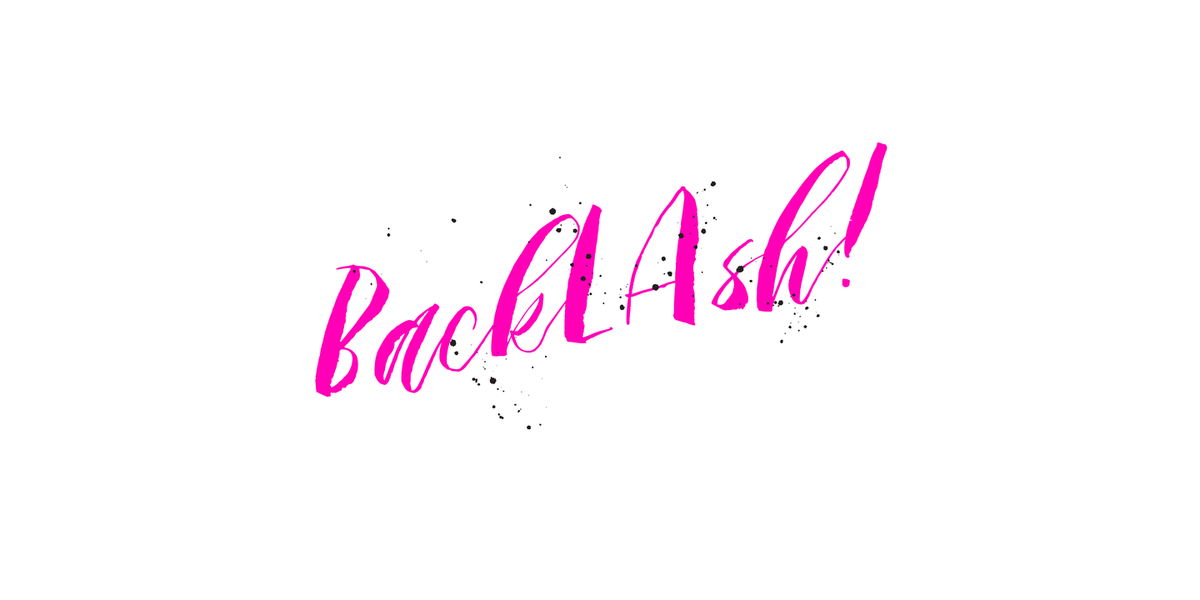
20 fuentes geniales escritas a mano para tus diseños
Cada sitio web tiene un objetivo final: hacer que las audiencias se relacionen con él para que cualquier llamado a la acción que tenga, lo seguirán con entusiasmo. Esto es lo que distingue a muchos sitios web.
Mientras que algunos optan por tomar la ruta más formal para enfatizar su enorme contribución a la industria a la que pertenecen, otros adoptan un enfoque más personal y optan por estar a la altura de las audiencias. Este último es donde las fuentes escritas a mano pueden ayudar mucho.
Las fuentes escritas a mano, desde el propio nombre, se basan en la escritura a mano real de personas. Esto significa que el equilibrio y la simetría pueden no tener nada que ver con su efecto general. Siempre que parezca que alguien lo escribió en un papel con un lápiz en lugar de escribirlo en el teclado de una computadora, se incluye inmediatamente en la categoría de fuentes escritas a mano.
¿Qué hace que las fuentes escritas a mano sean tan atractivas?
En un mundo donde casi todo se ha vuelto digital, a menudo es refrescante ver algo que se creó personalmente. Esta es una de las razones por las que las artes y la artesanía parecen estar ganando un gran número de seguidores en los últimos años. Es algo natural a lo que la gente puede aferrarse en medio de los productos comercializados.
Esto es exactamente lo que ofrecen las fuentes escritas a mano. Da la impresión de haber sido escrito personalmente, lo que hace que todo lo escrito con la fuente parezca más personal, más identificable, más efectivo.
¿Dónde se pueden utilizar estas fuentes escritas a mano? Casi todo, cuando lo piensas.
Los diseñadores que trabajan en blogs y páginas web personales pueden encontrar un gran uso para esto, porque representa mejor a las personas.
Sin embargo, si tiene mucho talento, puede usar cualquiera de estas fuentes escritas a mano incluso si está trabajando en un conjunto de páginas comerciales, especialmente si el propietario del sitio web desea crear una imagen más personal de su marca.
A continuación se muestran 20 fuentes geniales escritas a mano que puede usar para sus diseños. Son ideales para cualquier proyecto de diseño, sin importar el tema o estilo que requiera.
Podrían funcionar tanto en sitios web personales como comerciales, y también se verían muy bien en cualquier anuncio en línea. Estas fuentes también se pueden utilizar en carteles, logotipos, pancartas y otros diseños similares.
Cualquiera de estos puede incluso agregar sabor a un proyecto en el que ha estado trabajando que parece que le falta algo y podría ser la pieza final que ha estado buscando todo el tiempo.
Imogen Agnes por Set Sail Studios
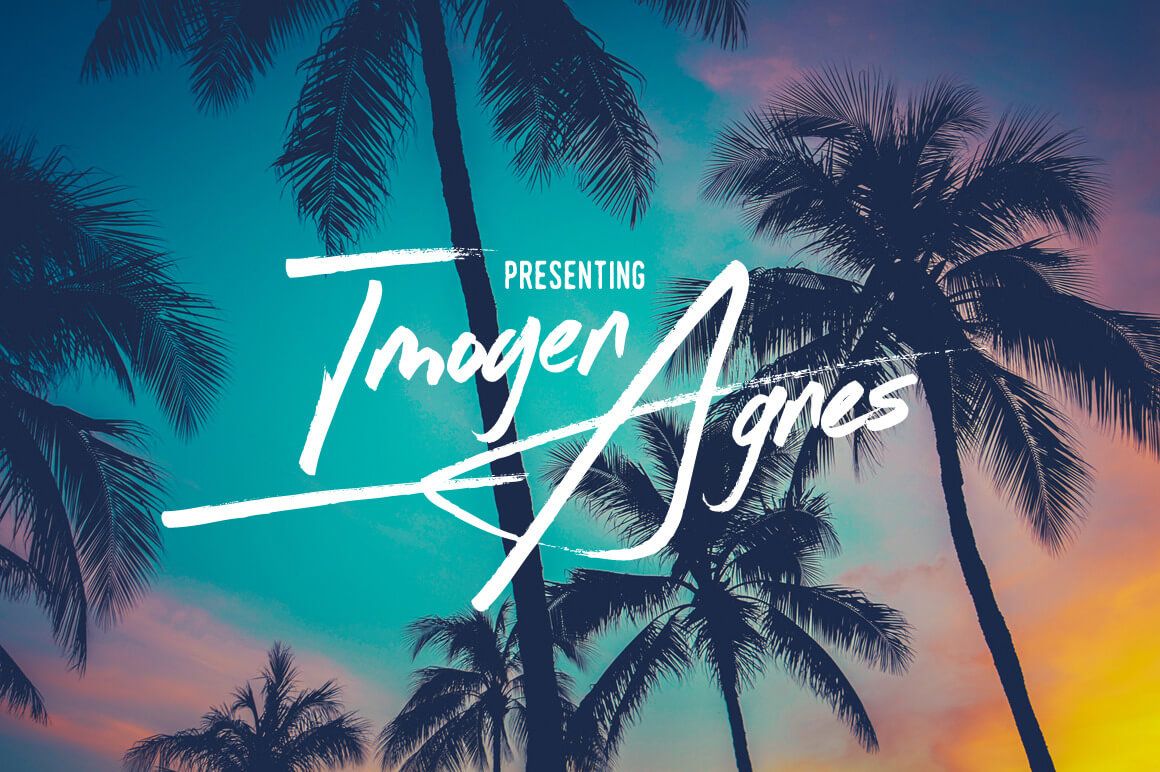
Imogen Agnes es una fuente de estilo de firma hecha a mano diseñada para crear letras personales y elegantes de forma rápida y sencilla.
Guión rápido de Efe Gursoy
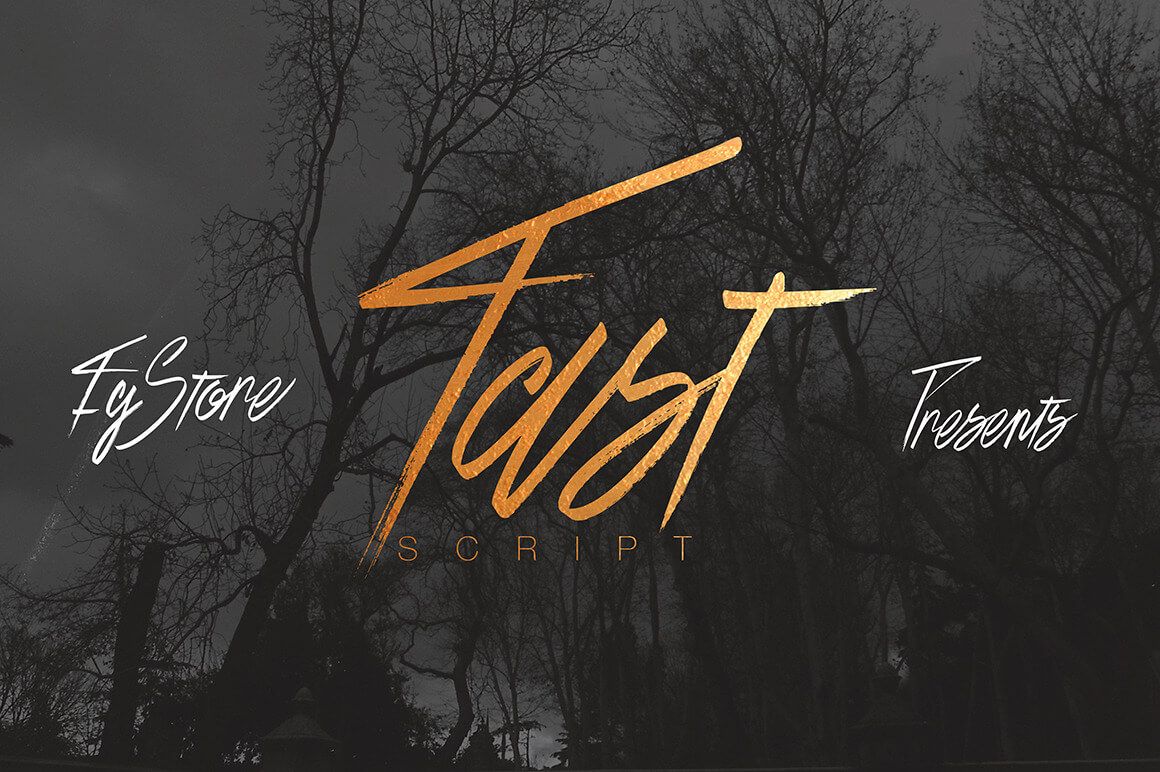
FastScript es una nueva fuente de graffiti hecha a mano.
Liniga de Graphite
Una tipografía manuscrita alta, cálida y amigable con una estructura simple y bajo contraste. Funciona bien tanto para la visualización como para el texto del cuerpo.
Unthrift by Aring Typeface
Unthrift, un tipo de letra de escritura de alta calidad, fue creado por Mans Greback en 2015. Fue construido con pinceladas grandes y vívidas e inspirado en la escritura a mano de los 90.
Tener corazón
Have Heart es un juego de 2 marcadores hechos a mano lápiz fuentes, diseñadas para combinar perfectamente y permitirle crear impresionantes letras a mano de forma rápida y sencilla. También se incluye un conjunto de 12 caracteres decorativos adicionales, ¡ideales para darle a su texto ese toque final de delicadeza!
Amado por Laura Worthington
Como corresponde a su nombre, Beloved Script sugiere la mano de un espíritu romántico ... aunque uno que escribe con un simple lápiz . Sus trazos monolinos evocan la caligrafía clásica del siglo XX lograda con un bolígrafo o plumilla redondeada.
Con más de 1000 caracteres decorativos y alternativas para elegir, incluidas mayúsculas, formas iniciales y finales, puede convertirse en un espectáculo bellamente decorativo, poderoso para titulares personalizados y marcas denominativas.
Rumi de ROHH
Rumi es una fuente de escritura con un toque orgánico y natural, diseñada para verse como una verdadera escritura a mano. Tiene un toque caligráfico y una ejecución temblorosa e impredecible, siendo muy clara y legible al mismo tiempo. Rumi tiene un conjunto de caracteres extendido de más de 900 glifos que contienen estilos alternativos, ligaduras estándar y discrecionales, símbolos, ordinales y formas que distinguen entre mayúsculas y minúsculas.
Hugo de Vitek Prchal
Hugo es una fuente enorme diseñada para títulos y encabezados llamativos. Es una familia tipográfica folk sans-serif tocada con un honesto sentimiento artesanal. Perfecto para títulos y encabezados notables, insignias, fotos superpuestas o cualquier cosa que necesite un texto en negrita inconfundible con un aspecto amable.
Paintlay de Mika Melvas
Paintlay es una fuente de escritura de pincel informal y relajada. La línea de base hinchable, los trazos erguidos y las formas suaves son las principales características de Paintlay. Lo que distingue a esta fuente de otras son las capas que incluyen la capa Base, dos capas de resaltado diferentes y dos capas de sombra.
Maris de insigne
Maris es una escritura rica y elegante, sutilmente caracterizada por una caprichosa caligrafía manuscrita. La familia está compuesta por seis pesos diferentes, cada uno más atrevido que el anterior pero todos igualmente llenos.
Los pesos más ligeros se mueven delicadamente a través de cada línea, mostrando una fuerza suave en su marco más pequeño. Los seis pesos desde estas formas más ligeras hasta las audaces incluyen algunas versiones texturizadas como jean, madera, estampados, rugosos y medios tonos.
Goodlife de HVD Fonts
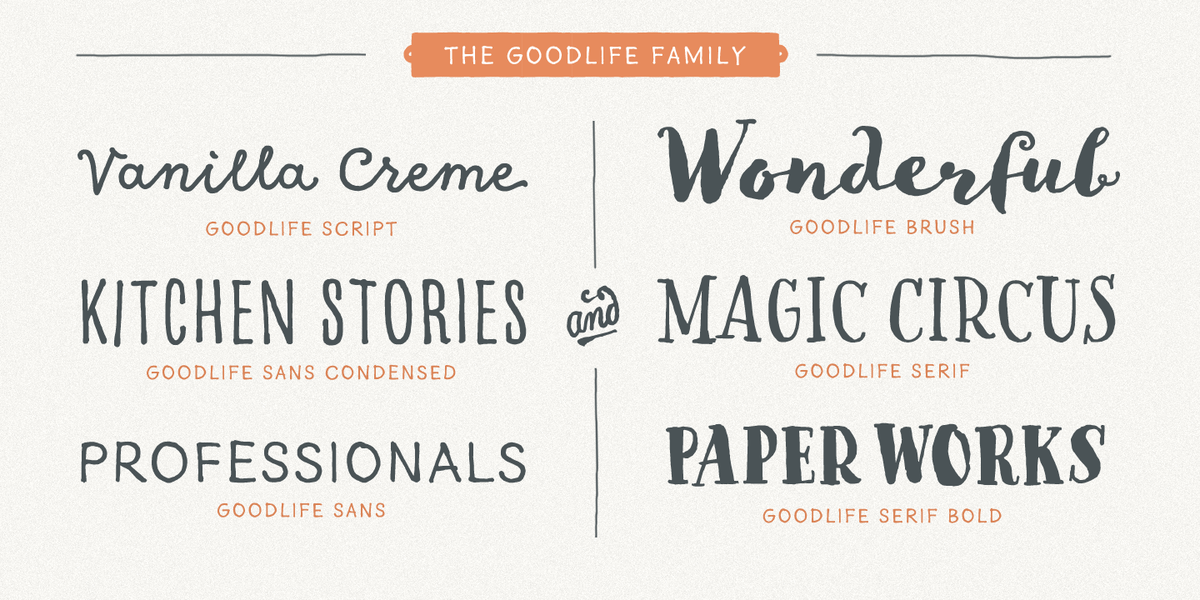
La familia tipográfica Goodlife es una hermosa colección de letras a mano diseñada por Hannes von Döhren. Contiene seis fuentes diferentes dibujadas a mano con un montón de características y un conjunto de extras como consignas, flechas, adornos y más.
Con este juego y un poco de amor y cuidado es posible crear hermosos gráficos 'hechos a mano'. Equipado con alternativas de intercambio automático, ligaduras, formas finales, letras swash y algunas otras características, Goodlife está optimizado para sentirse no solo como una fuente sino como verdaderos boletines.
Sabores Script por Latinotype
Sabores es una fuente de escritura deliciosa inspirada en los sabores del mundo de la cocina. Se basa en formas suaves y curvas orgánicas. La familia contiene 5 pesos con cursiva y caracteres decorativos. También se incluyen algunos deliciosos dingbats. Sabores es ideal para logotipos, marcas, envasado de alimentos , restaurantes, cafeterías, panaderías, festivales gastronómicos, menús, títulos de libros, etc.
Stylist Pro de Fontforecast
Conoce a Stylist Pro, una familia de fuentes con interesantes trucos de estilo bajo la manga. Puede mezclar letras mayúsculas con minúsculas de la forma que desee y obtener resultados interesantes.
Al usar mayúsculas, puede activar y desactivar ligaduras discrecionales para tener en sus manos algunas hermosas combinaciones de letras de arriba a abajo. Elija Ligaduras estándar para activar pares entrelazados para mayúsculas.
Hola hermosa de Nicky Laatz
Presentamos un dúo de fuentes escritas a mano, cuidadosamente diseñadas para trabajar juntas en armonía para crear diseños tipográficos magistrales en un instante.
29 de agosto zodiaco
Faith & Glory de Set Sail Studios
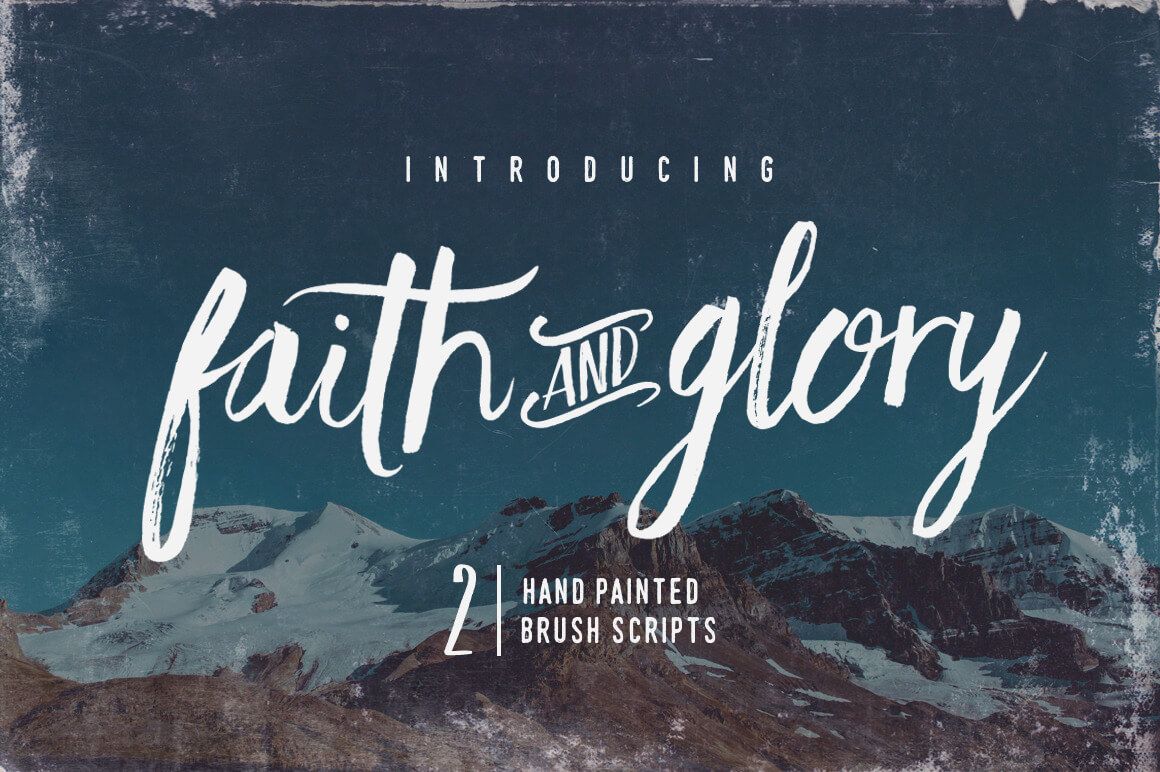
Faith and Glory es un conjunto de 2 fuentes de pincel pintadas a mano, diseñadas para combinarse perfectamente entre sí y permitirte crear una hermosa tipografía con un toque personal. La fuente viene con caracteres en mayúsculas y minúsculas como dos fuentes separadas, puntuación, números y admite idiomas internacionales.
Reacción por las letras de los Grandes Lagos
Backlash es una fuente de estilo script pintada a mano que agrega un factor de enfriamiento instantáneo a cualquier proyecto. Esta fuente se esfuerza por aportar un toque real ilustrado a mano a los diseños, ya que la variación en los grosores de las líneas, las texturas y las formas de las letras crea una pieza final única. Estas variaciones también crean un movimiento enérgico a lo largo de las palabras y, junto con una variedad de salpicaduras de tinta, está listo para contraatacar.
Lolapeluza de RodrigoTypo
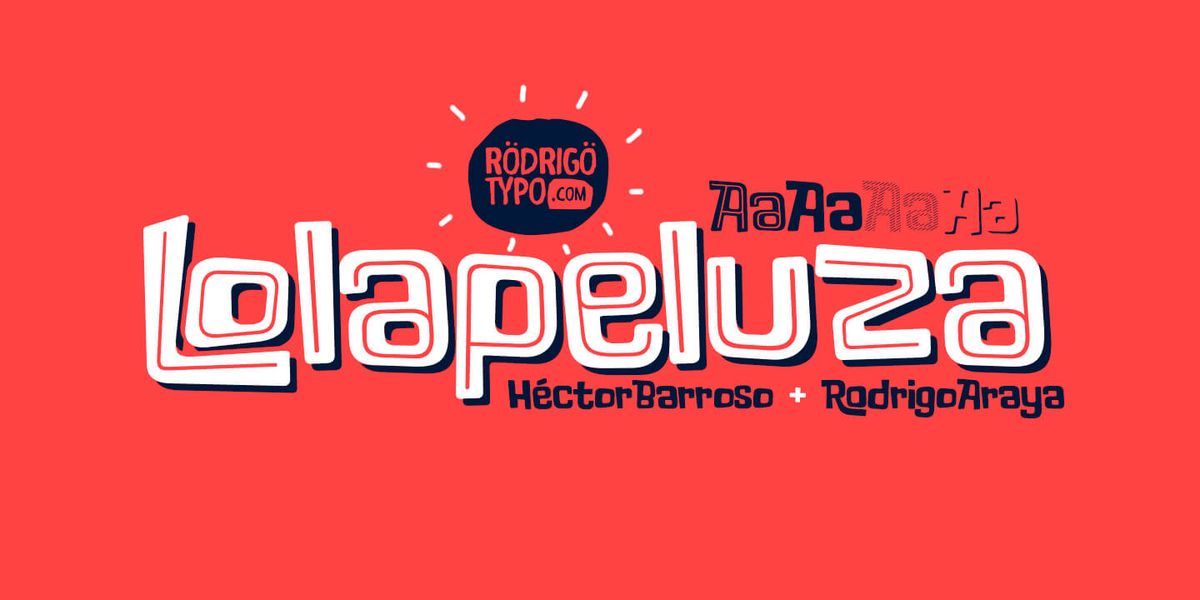
Inspirado en el logo de “Lollapalooza”. La intención era diseñar una tipografía alegre y entretenida. Lolapeluza funciona perfectamente para diseños para niños y jóvenes.
Snow Cone Pro de Fontforecast
Snow Cone Pro es una familia de fuentes dibujadas a mano que consta de 6 tipos de letra divertidos. Snow Cone Pro aporta un toque fresco de verano a tus diseños. Puede cambiar la apariencia de cada fuente jugando con las características de tipo abierto, como pares entrelazados, ligaduras de letras dobles, alternativas estilísticas.
Goma de mascar de PintassilgoPrints
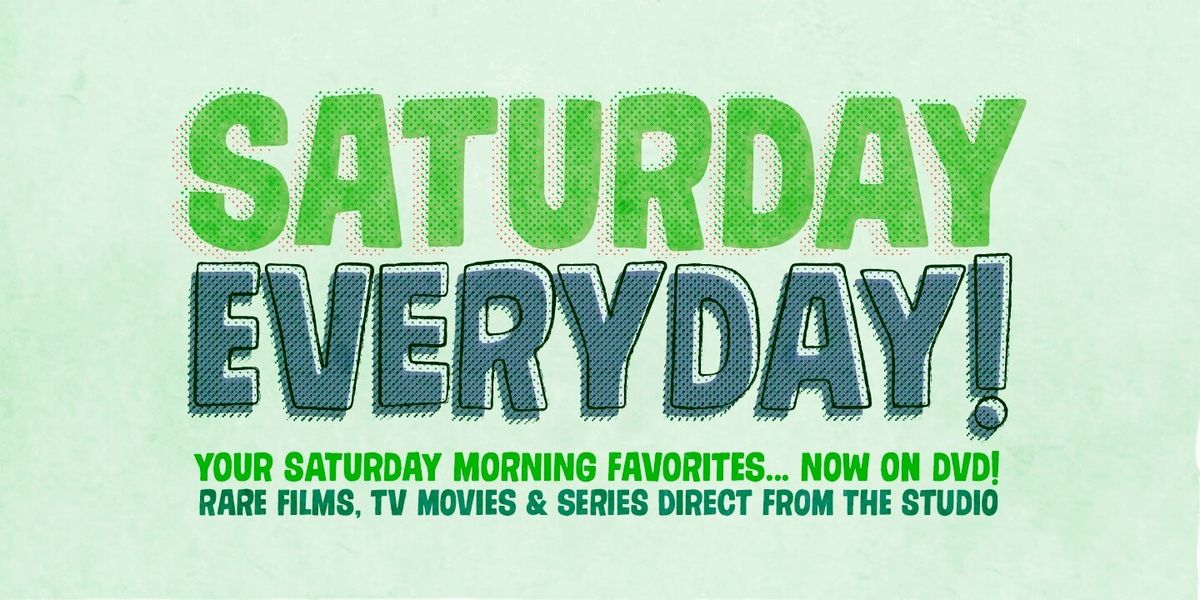
Gumdrop es un sans suave. Elegante, original y un poco retro, es una fuente en mayúsculas con dos opciones para cada letra y número para mayor espontaneidad. La función de alternativas contextuales está incluida y administra el ciclo instantáneo de estas alternativas con el clic de un botón.
Mezclar por tipos de letra
Esta fuente en capas está aromatizada con el espíritu artesanal que caracteriza a todas las fuentes Typesenses y es quizás la que más muestra la mano de su autora, Sabrina M. Lopez.
Aunque esta linda colección toma elementos del universo visual de Panaderías y Cafeterías, es solo una metáfora. Puedes crear tu propio look y utilizarlo para logos, revistas, menús, libros para niños, invitaciones, tarjetas de boda / felicitación, packaging, etiquetas, bodega, etc. Todos tus diseños tendrán un bonito toque casero con Blend.